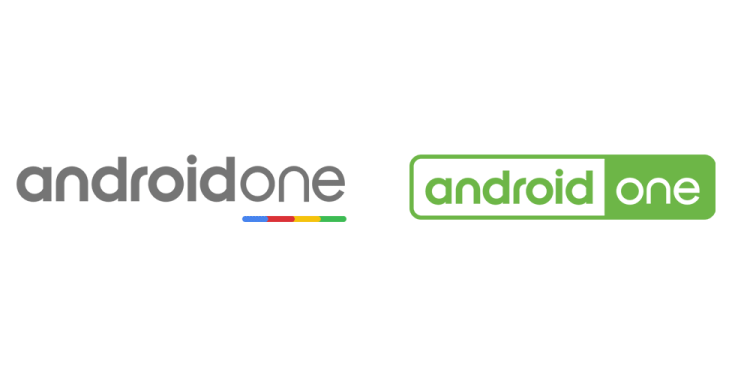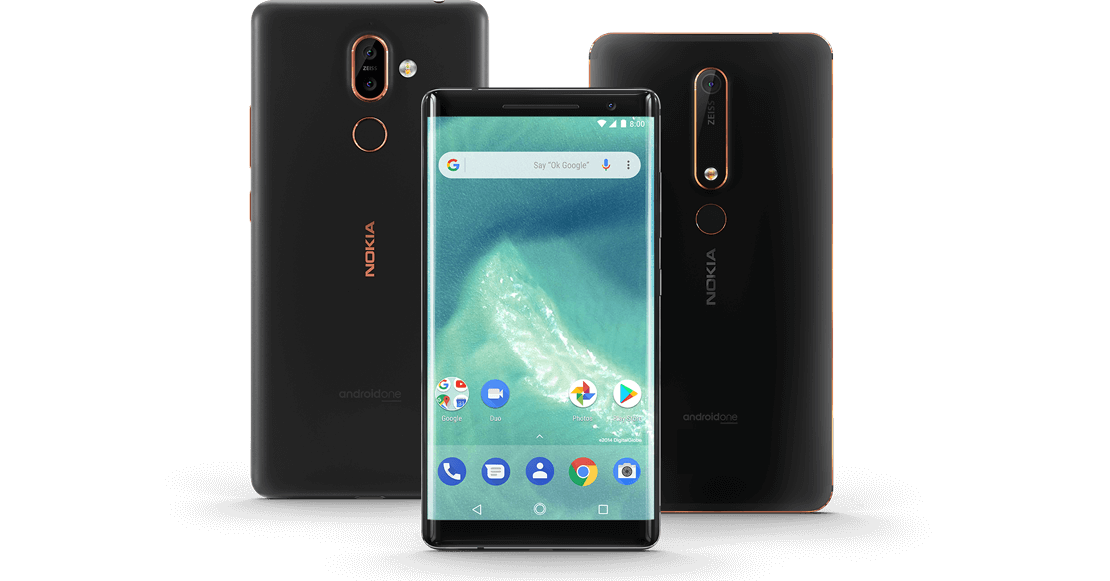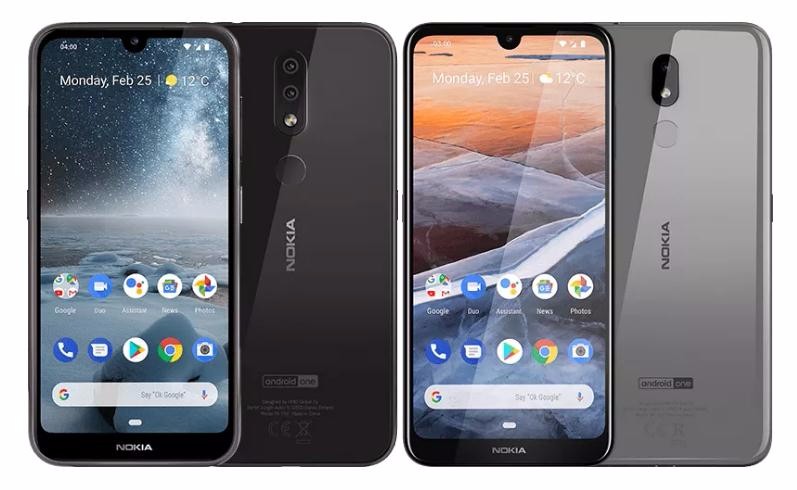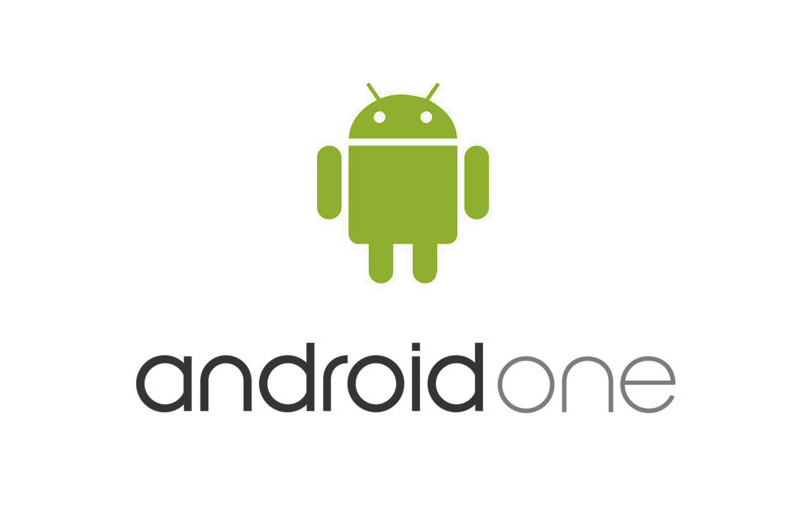
谷歌推出新品牌标志 Android One new logo
Android One是搭载Android系统的系列电子产品,由谷歌开发,产品搭载原生Android系统,主要面向发展中国家推出。
Android One发布了已经好几年了,产品也推出了数十个之多。最近,谷歌悄悄地为Android One设计了新的标志。
Android One新标志去除了之前的四色线条,采用单一的绿色,这有点类似于安卓LOGO机器人的绿;一白一绿两个框将Android和One分开,更加突出One这个词。目前谷歌已经在官方网站上用上了Android One标志。
标志的变化是为了展示更清晰起见,这样可以更好地应用在智能手机上。标志会在每台Android One设备的背面标示,而之前的设计,因为有谷歌标志性的四色,当展示时没有彩色时标志看起来会有偏差。而新的标志在设备背面只需以一种颜色印刷,看起来更完整清晰。
新近推出的诺基亚3.2和诺基亚4.2,将这个新标志带到了大家的面前,这两台手机都将标志刻在了背面。蹊跷的是,诺基亚同一天的另一个发布会用的仍然是旧标志。
这是Android One早期使用的标志。